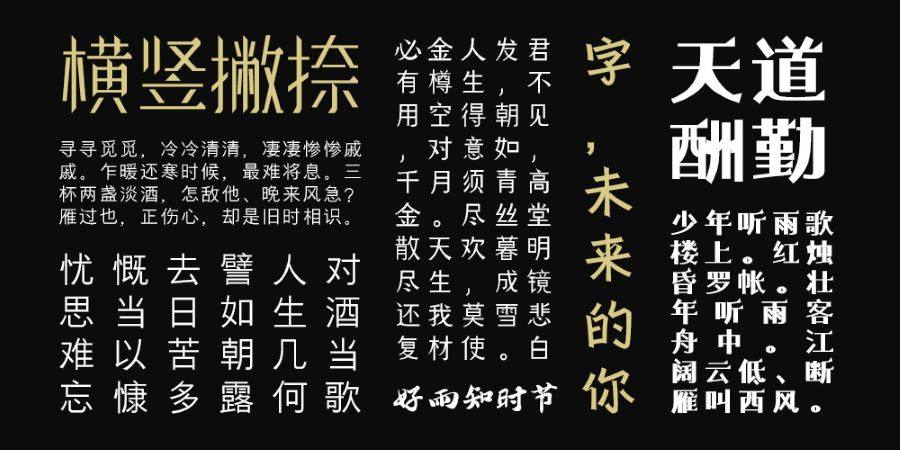
相信很多的人在平时写东西的时候经常会用到方正字库兰亭字体,那么这种字体究竟有什么特点才会让我们广泛的使用呢?大家是不是也都很好奇,为什么我们不直接用宋体或者其他样式的字体呢?那么下面我们就一起来看看吧。
我们在用电脑写东西的时候大多数时候,一般叙事或者写一些论文用的就是普通的字体,而我们最常用的可能是宋体。因为它没有任何的设计完全就是最普通的字体形式,当然我们平时用的最多的就是这种。如果我们用太多的艺术字在正常的文章当中就不便读者的阅读了,当然我们还可以用的是兰亭字体,这种字体跟宋体的字体差不多,但是不会像宋体字那样的死板,一点设计感都没有。
这种字体的设计感特别的微妙,你如果不细看的话很难跟宋体区分开来。但是我们就是在读或者用这种字体写字的时候觉得很舒服,仿佛在哪用了不同的设计,但是又不太明显的感觉。其实兰亭字体也分好几种,有粗的有细的。而我觉得细的更能看出它的字体设计特点,它字体里面的留白空间会比较大,所以看起来字特别的干净,又不会很紧凑的样子。
这样的字体就让人不会读起来觉得很死板,让人看起来觉得很舒服,但是又不会让人觉得字体特别的刻意,在看这种字体的时候会更多的把注意力集中在字体上而不是内容上。这样的字体其实还是比较大众化的,使用的人数也比较多,因为它就是根据大众的喜好设计的。